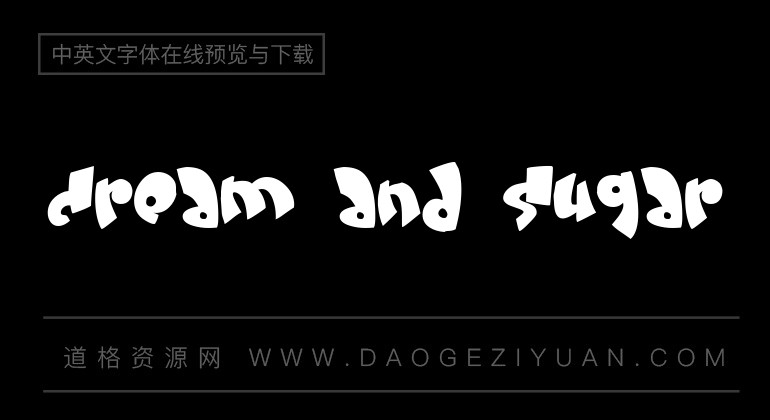
Cream and sugar
Cream and sugar是一款自然而古典的字体,它的外观温和可爱,拥有清晰的线条和古典的细节,适合用于各种类型的设计。它的特点是可以在平面设计中创造出柔和、舒适的感觉,使得设计更加具有质感和温暖的气息。
Cream and sugar是一款非常不错的手写艺术字体,具有很好的视觉感,适合于文化类的宣传设计、商业类品牌的广告和产品包装设计以及个性化文字排版等较多场景。